ESport, singkatan dari electronic sports, telah meroket menjadi salah satu industri hiburan terbesar di dunia. Pertandingannya sering kali menarik jutaan penonton dari seluruh penjuru dunia, dengan turnamen-turnamen besar yang menawarkan hadiah yang fantastis. Di balik ketenarannya, logo eSport menjadi salah satu aspek kunci dalam membangun identitas tim yang kuat.
Namun, desain logo eSport tidaklah lengkap tanpa pemilihan font yang tepat. Dengan font terbaik, logo eSport dapat menjadi ikonik dan mudah diingat oleh para penggemar. Dalam artikel ini, kami telah mengumpulkan 37 font logo eSport paling keren yang dapat Anda unduh dan gunakan secara gratis untuk desain Anda! Yuk, langsung saja simak daftar font-nya di bawah ini!
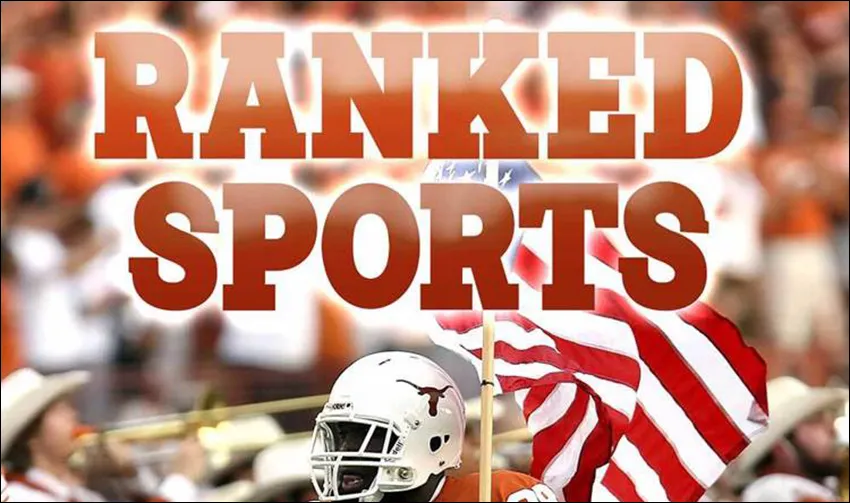
Font pertama adalah Ranked Sports. Font slab-serif ini memiliki desain bold dengan kesan yang serius dan kompetitif, cocok untuk permainan yang menekankan kompetisi seperti game-game football atau yang lainnya.
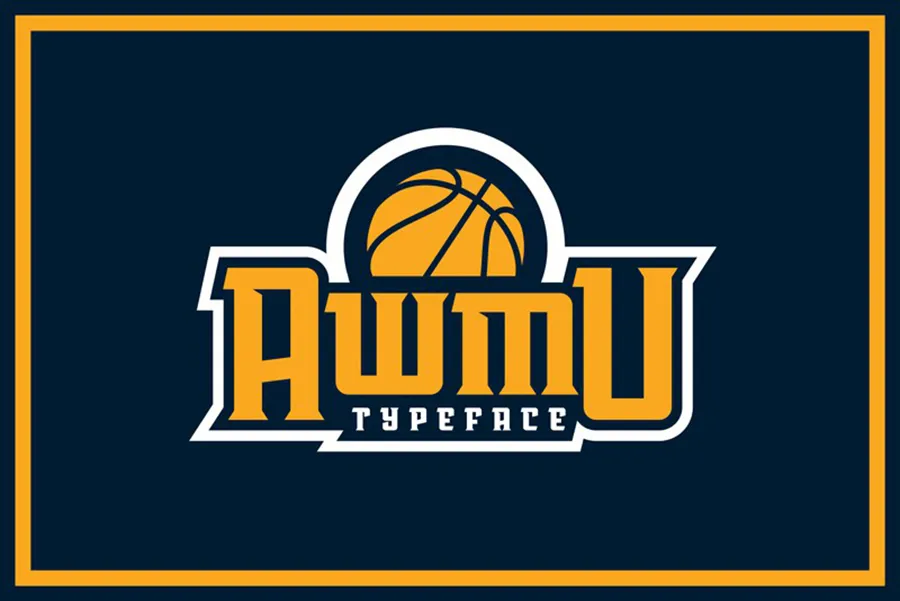
Font kedua adalah Awmu. Font ini memiliki gaya yang modern dan futuristik, cocok digunakan untuk game-game eSport dengan tema cyberpunk atau sci-fi yang menuntut kecepatan dan strategi.
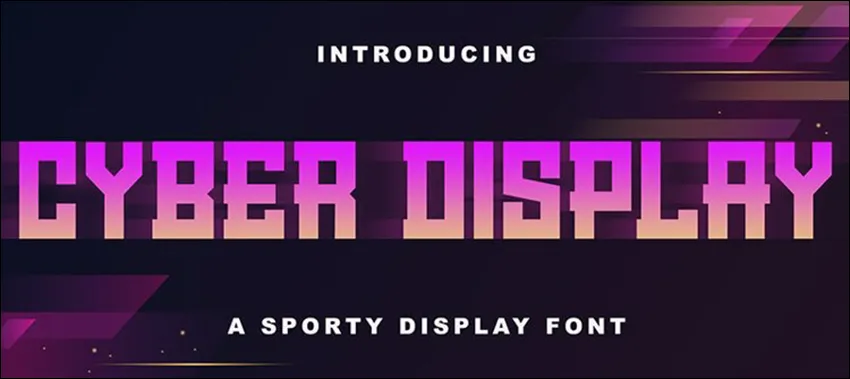
Selanjutnya adalah font Cyber Display. Font sans-serif ini memiliki desain techno yang mencolok dan futuristik, ideal untuk permainan dengan tema teknologi tinggi di dunia virtual atau cyber, sebagaimana namanya.
Dengan gaya modern pixelated, font ini cocok digunakan untuk game-game eSport atau game-game indie yang menampilkan grafis pixelated.
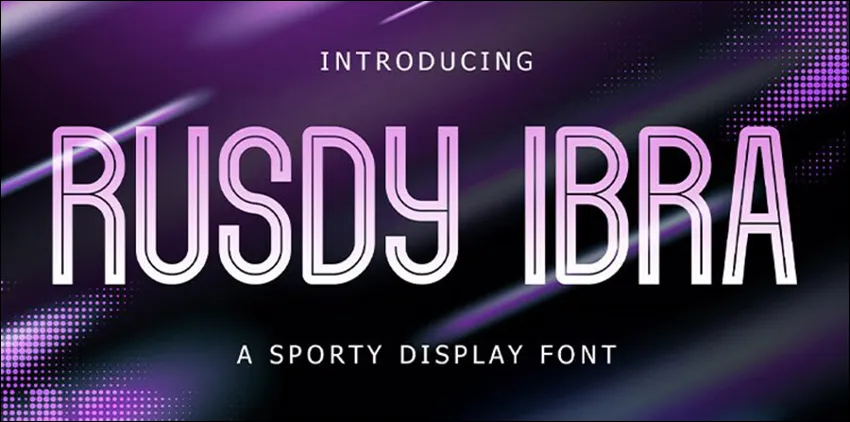
Font sans-serif ini memiliki desain yang unik dan artistik, cocok digunakan untuk permainan eSport yang menonjolkan kreativitas dan keunikan, seperti game-game puzzle atau platformer.
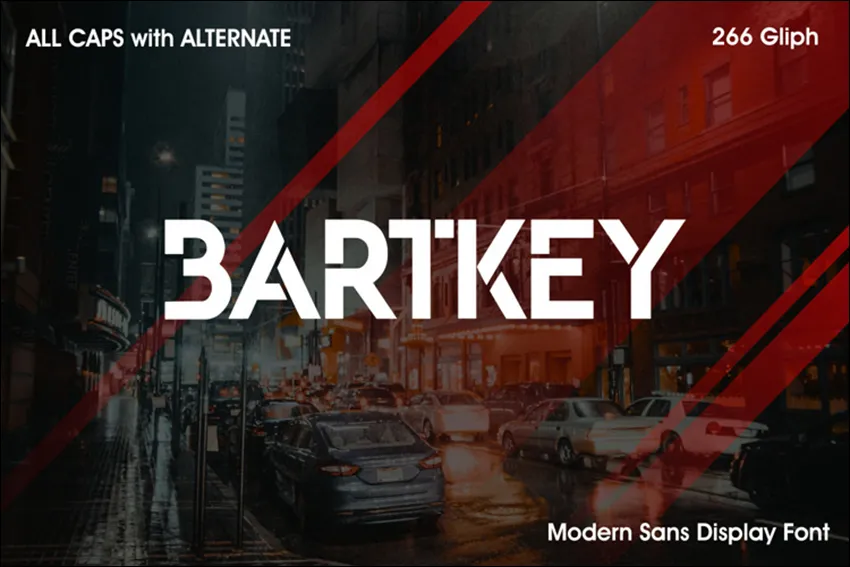
Dengan desain yang dinamis dan modern, font ini cocok untuk game-game eSport yang menekankan kecepatan dan aksi seperti game balapan atau shooter.
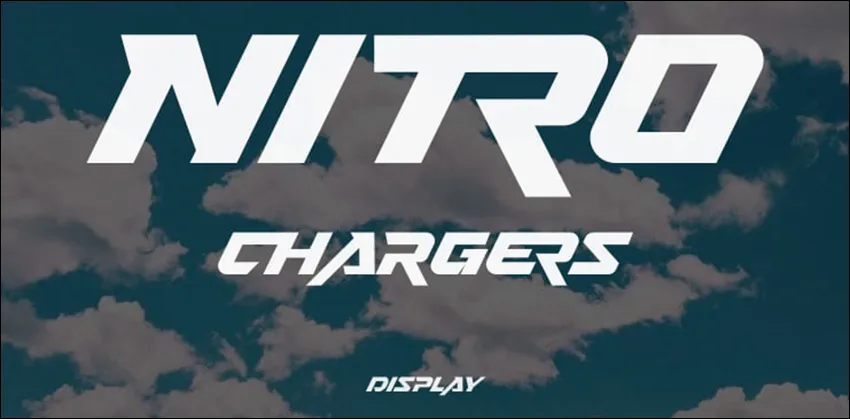
Font ini memiliki desain yang energik dan agresif, cocok untuk game-game eSport yang menampilkan aksi cepat dan adrenalin tinggi seperti game-game balap mobil atau FPS.
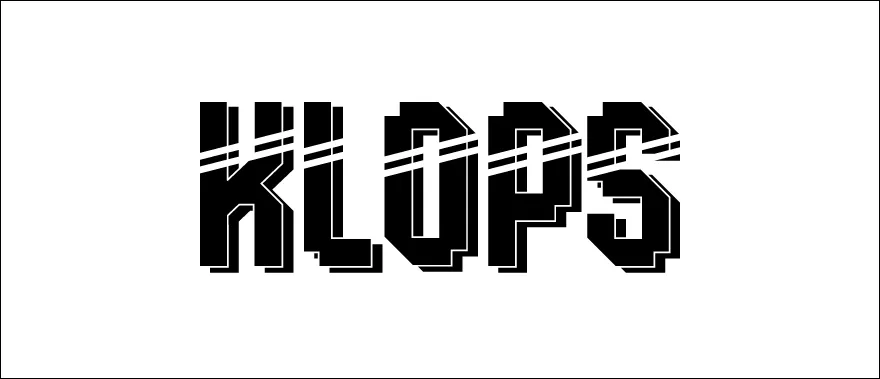
Dengan desain yang simpel namun kuat, font ini cocok untuk game-game eSport yang menonjolkan kekuatan dan keberanian, seperti game-game pertarungan atau battle royale.
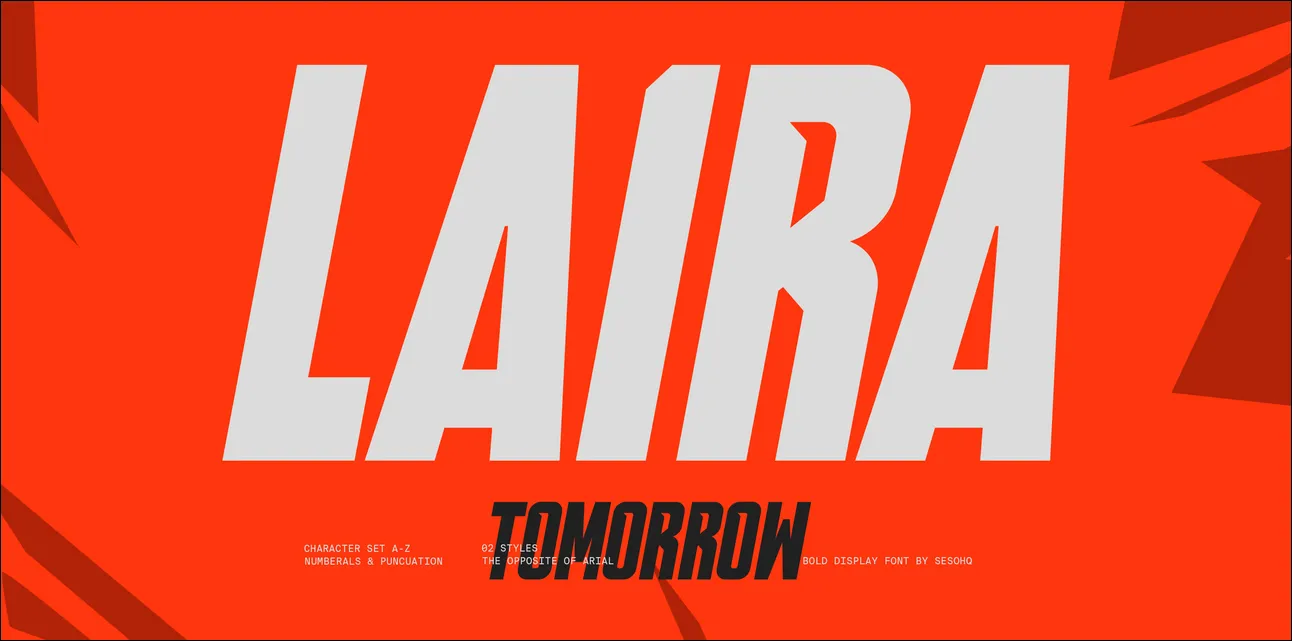
Font ini memiliki desain yang elegan dan eksklusif, cocok untuk game-game eSport yang menekankan strategi dan taktik, seperti game-game strategi atau permainan kartu.
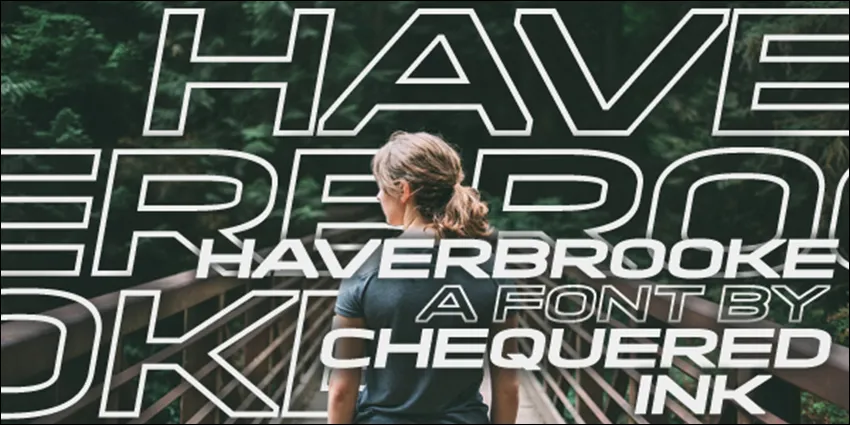
Dengan desain yang bersih dan modern, font sans-serif ini cocok untuk game-game eSport yang menampilkan keahlian dan presisi, seperti game-game olahraga atau simulasi.
Font ini memiliki desain yang dinamis dan cepat, cocok untuk game-game eSport yang menonjolkan kecepatan dan refleks, seperti game-game balapan atau permainan arcade.
Font ini memiliki desain yang dinamis dan energik, cocok untuk game-game eSport yang menampilkan kecepatan dan persaingan, seperti game-game balap mobil atau motor.
Dengan desain yang agresif dan modern, font ini cocok untuk game-game eSport yang menekankan kekuatan dan ketangkasan, seperti game-game pertarungan atau olahraga ekstrem.
Font ini memiliki desain yang unik dan eksentrik, cocok untuk game-game eSport yang menonjolkan kreativitas dan keunikan, seperti game-game puzzle atau platformer.
Dengan desain yang kuat dan agresif, font slab-serif ini cocok untuk game-game eSport yang menampilkan pertarungan atau adu kekuatan, seperti game-game pertarungan atau battle royale.
Font ini memiliki desain techno yang kuat dan mencolok, cocok untuk game-game eSport yang menampilkan kekuatan dan aksi, seperti game-game pertarungan atau olahraga ekstrem.
Dengan desain geometris yang unik, font ini cocok untuk game-game eSport yang menekankan kompetisi dan pencapaian, seperti game-game olahraga atau strategi.
Font ini memiliki desain yang dinamis dan energik, cocok untuk game-game eSport yang menampilkan kecepatan dan persaingan, seperti game-game balap atau permainan aksi.
Dengan desain yang unik dan karakter-karakter yang kuat, font ini cocok untuk game-game eSport dengan tema misteri atau lainnya.
Font ini memiliki desain yang mewah dan eksklusif, cocok untuk game-game eSport yang menampilkan kemewahan dan keanggunan, seperti game-game simulasi atau strategi.
Ya, warna dan font pada logo eSport seringkali saling berhubungan untuk menciptakan kesan keseluruhan yang konsisten dan menarik. Pemilihan warna yang sesuai dengan karakteristik font dapat meningkatkan daya tarik visual dan membantu menciptakan identitas yang kuat untuk tim atau organisasi eSport tersebut.